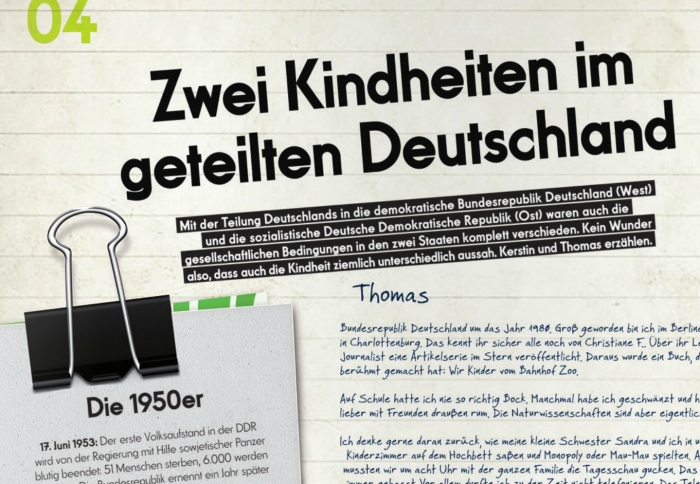
im aktuellen spiesser.de ist diese Schriftart verwendet worden. Ich tippe ganz stark auf eine Fundamental Grotesk, bin mir aber nicht sicher, denn die ist ja nicht so professionell digitalisiert worden. Die 7 hat einen Quersteg und die 5 sieht auch stilistisch aus. Kann mir jemand helfen? Ich wünsche Euch allen ein schneefreies Wochenende  ;-)
vielen Dank für Deine Antwort. Die Frage ist nur, gibt es den Font auch professionell? Ich frage mich, ob eine Zeitung Schriften nutzt, die ein Privatmann konstruiert hat?
Laut dem hiesigen Font-Wiki sind keine aktuellen Digitalisierungen der Fundamental Grotesk bekannt. Weitere Infos zu Peters Version findest du in diesem Thread. Ob in dem von dir gezeigten Beispiel die Fundamental Brigade zum Einsatz kam, müsstest du beim Spiesser erfragen: info (at) spiesser.de.
Die Frage ist nur, gibt es den Font auch professionell? Ich frage mich, ob eine Zeitung Schriften nutzt, die ein Privatmann konstruiert hat?
Deine Einschätzung verwundert mich, ehrlich gesagt. Ich würde Peter Wiegel in Sachen Schriftgestaltung jetzt nicht als Privatmann bezeichnen – jedenfalls nicht, wenn dem eine negative Konnotation in Sachen Schriftgestaltung anhaften sollte. Er ist geschätzter Kollege hier im Forum, »alter Hase« in Sachen Schriftgestaltung und ist mit seinem professionellen Wissen und Können ganz sicher vielen anderen Gestaltern voraus. Seine Schriften werden regelmäßig verwendet für professionelle Projekte, zum Beispiel im Filmbereich, wo seine digitalen Interpretationen alter Schriften eine wichtige Lücke in Sachen Authentizität schließen. Warum also die Bedenken?
Und damit wir hier alle auf derselben Grundlage debattieren: die augenscheinlichen Merkwürdigkeiten (wie das s mit den unterschiedlich ausgeführten Strichenden) sind i.a.R. nicht auf Peters Mist gewachsen, sondern schon in der bleiernen (und zumindest in einigen Schnitten »miserabel« zugerichteten) Fundamental Grotesk. Von daher ist die Brigade wohl einigermaßen authentisch: